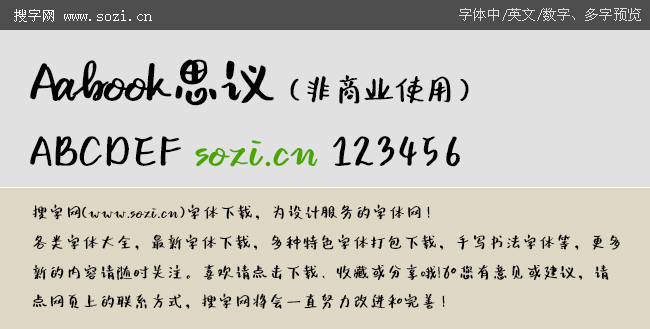
Aabook思議
搜字網(wǎng)給大家提供一款A(yù)abook思議(非商業(yè)使用)中文字體下載,Aabook思議是一款略帶卡通風(fēng)格的手寫(xiě)字體,字形可愛(ài)俏皮,透出一些稚氣。書(shū)寫(xiě)上融入了連筆,活潑靈動(dòng)。適合應(yīng)用于藝術(shù)設(shè)計(jì)、平面宣傳設(shè)計(jì)、網(wǎng)頁(yè)設(shè)計(jì)、海報(bào)設(shè)計(jì)等應(yīng)用(此字體為個(gè)人非商用版,商用可以聯(lián)系QQ:1006760504)。